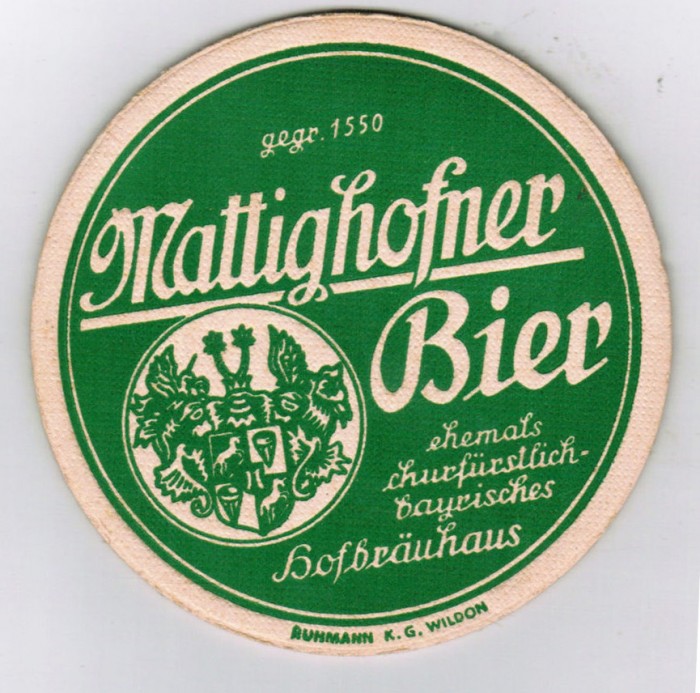
Mattighofner Bier
Kennt jemand diese Schrift oder kann mir eine ähnliche (vorzugsweise etwas moderner) empfehlen? Die Brauerei wurde 1975 geschlossen, davor wurde die Schrift anscheinend schon eine zeitlang nicht mehr verwendet, das Design könnte also vielleicht aus den 50ern stammen. Mattighofen liegt in Oberösterreich.